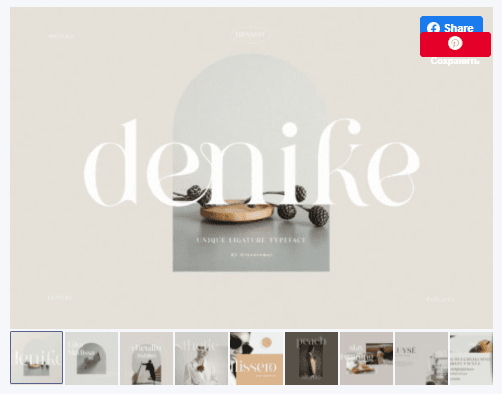
Denike Font
Denike - это современный шрифт с засечками, в котором используются смелые и элегантные символы. Его сильный внешний вид и яркая индивидуальность делают этот шрифт отличным выбором для газет, обложек книг, баннеров, визиток, маркетинга и многого другого!